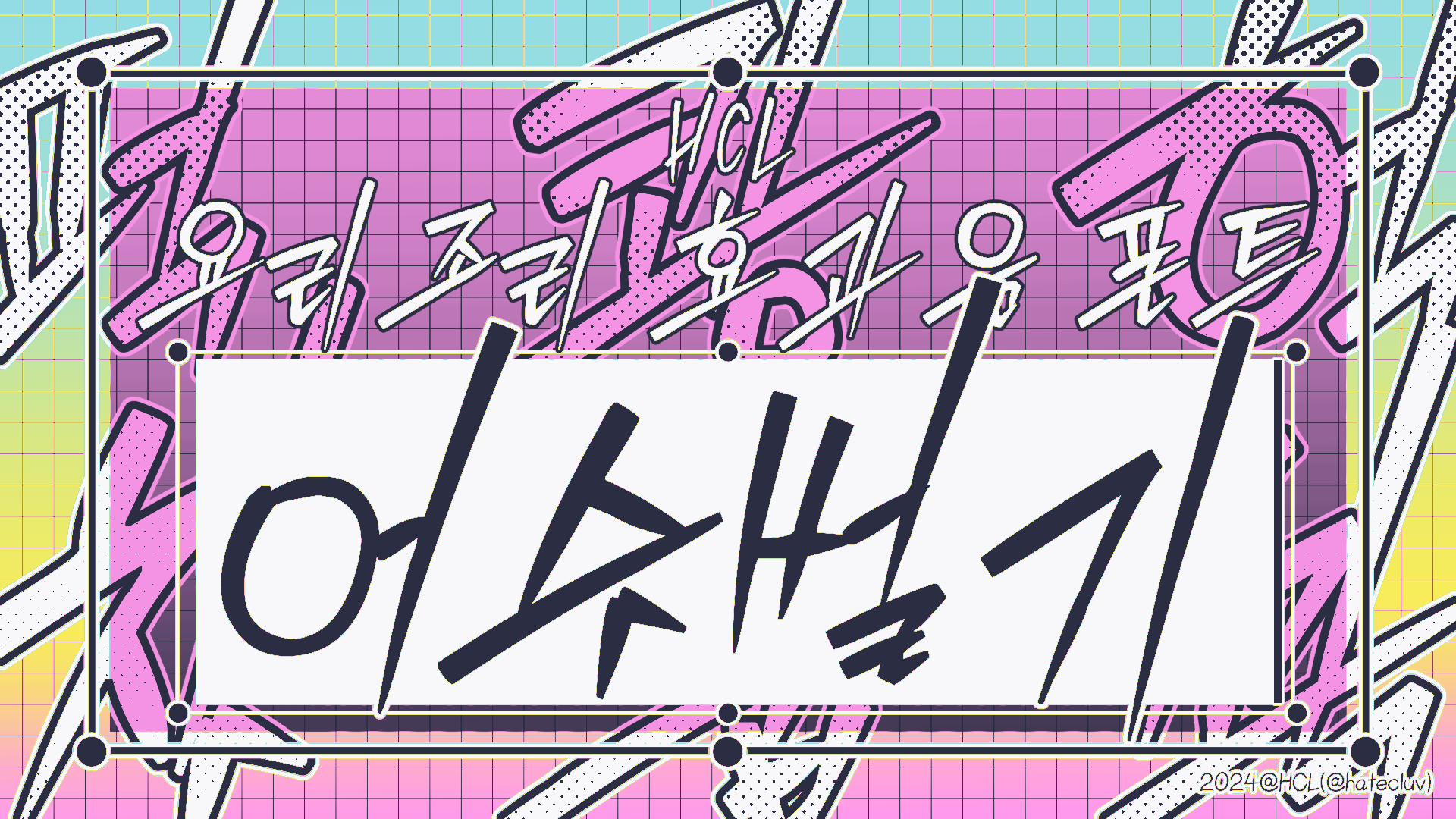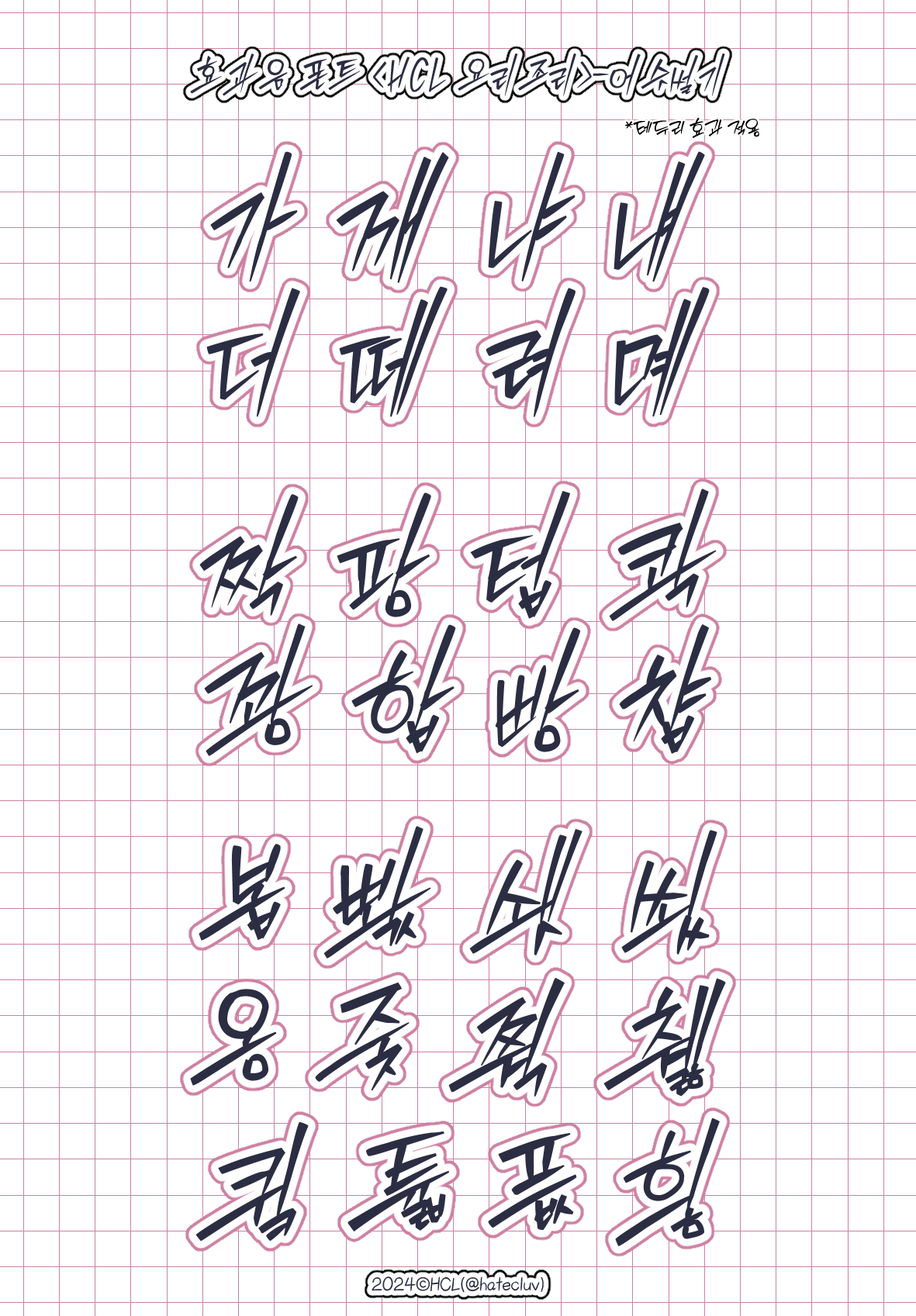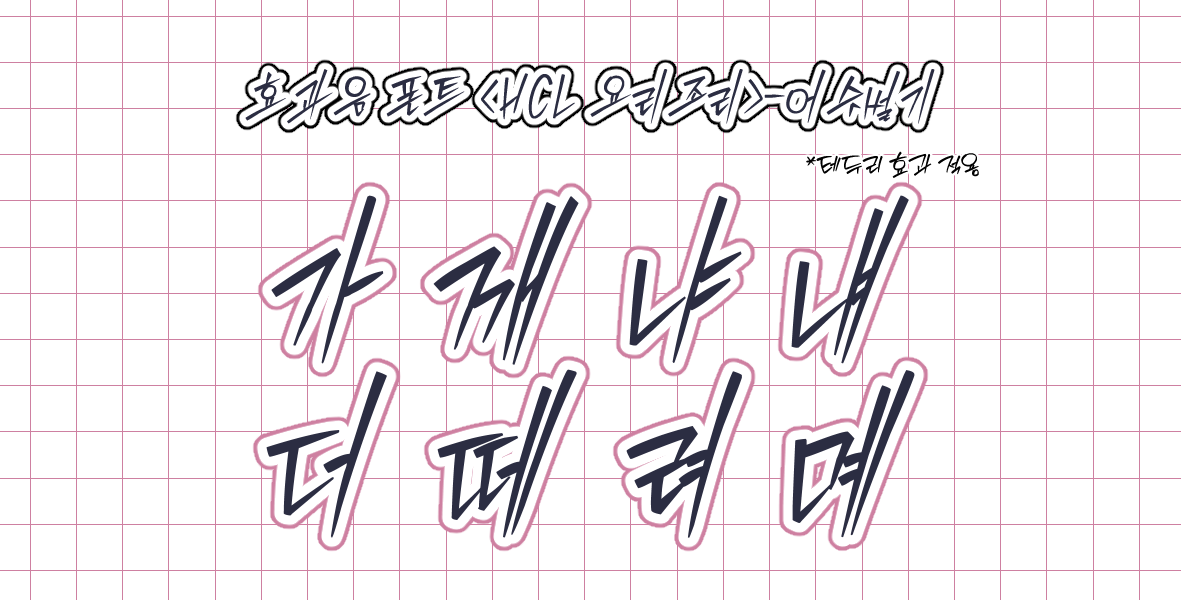
만화 효과음 느낌의 캘리그라피 폰트 5종 시리즈 <HCL 요리조리> 중 <어썰기> 입니다. 한 쪽으로 쏠린 무게감과 긴 모음 디자인으로 소리를 강조하는 연출에 사용하면 좋습니다.
디자인 특성 상 만화 효과음 용도 외 디자인, 문서 작업 등에서는 가독성이 떨어집니다.
HCL 요리조리 어슷썰기